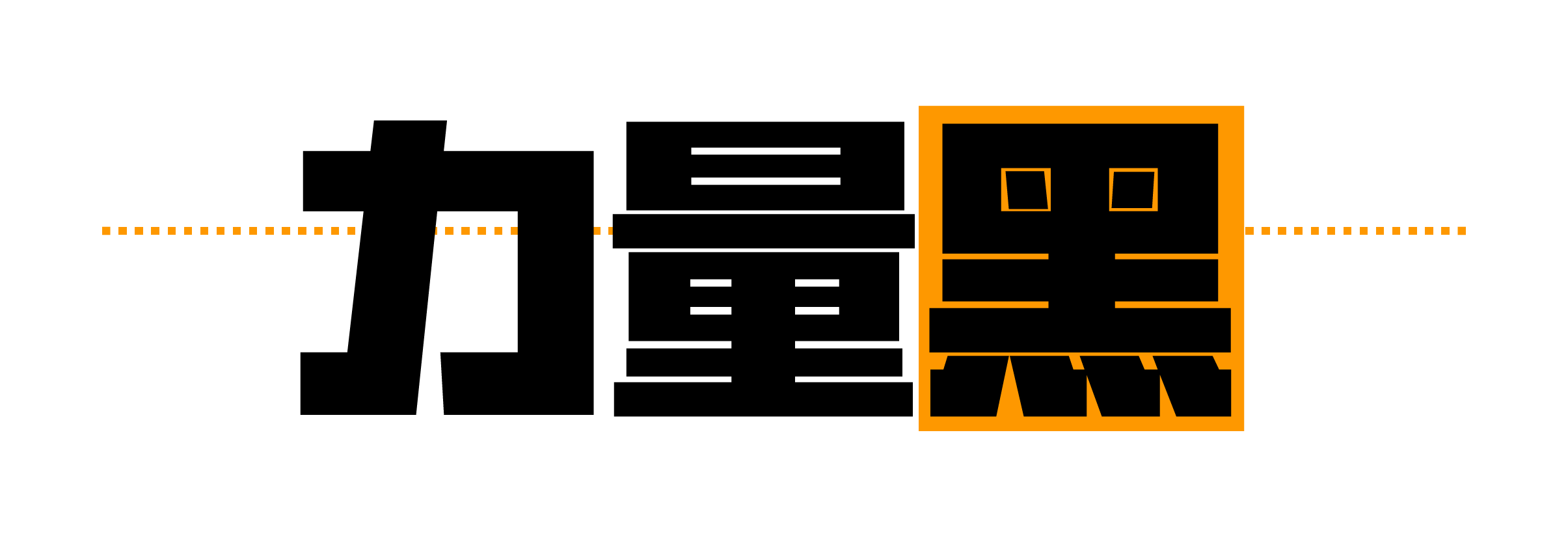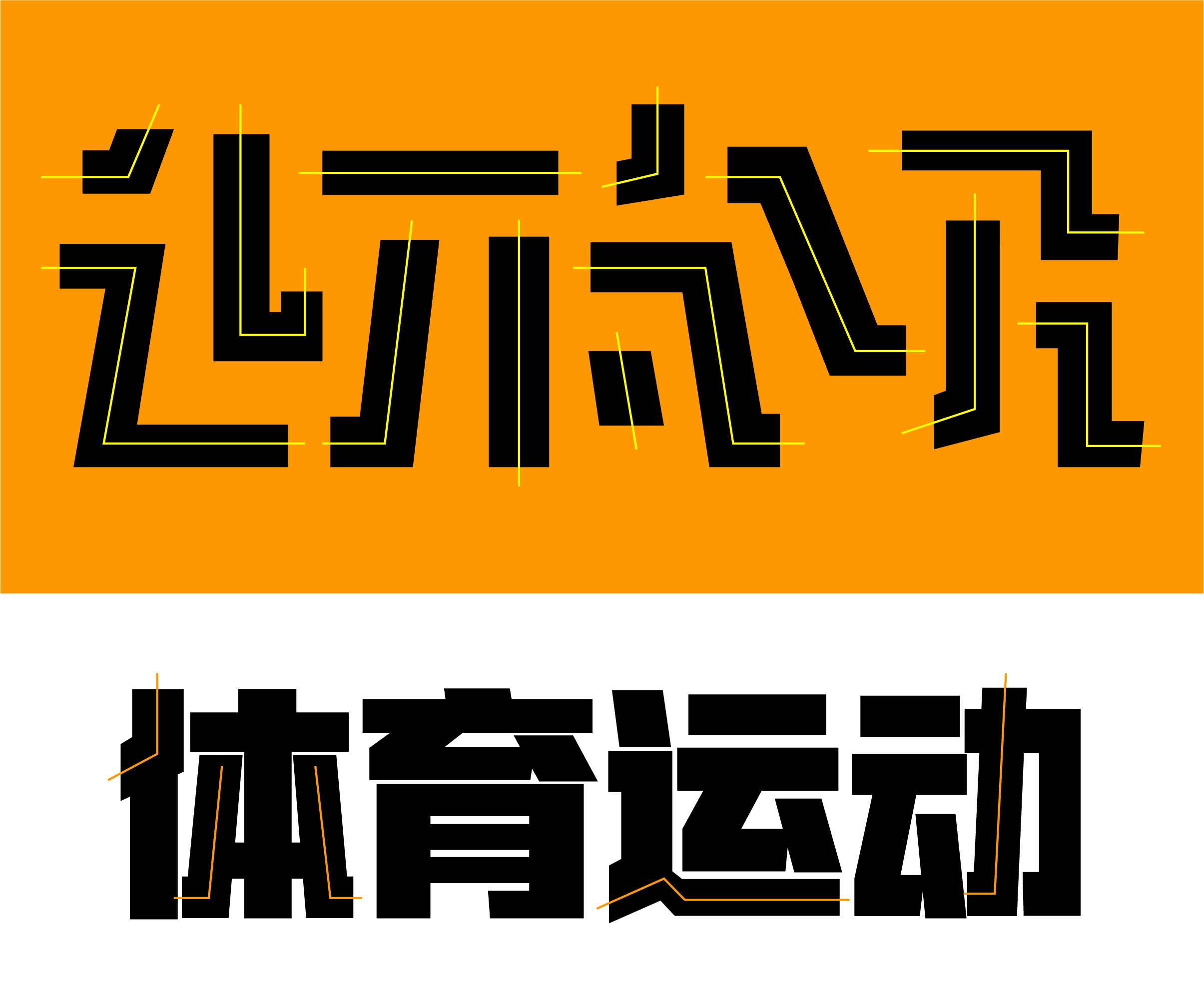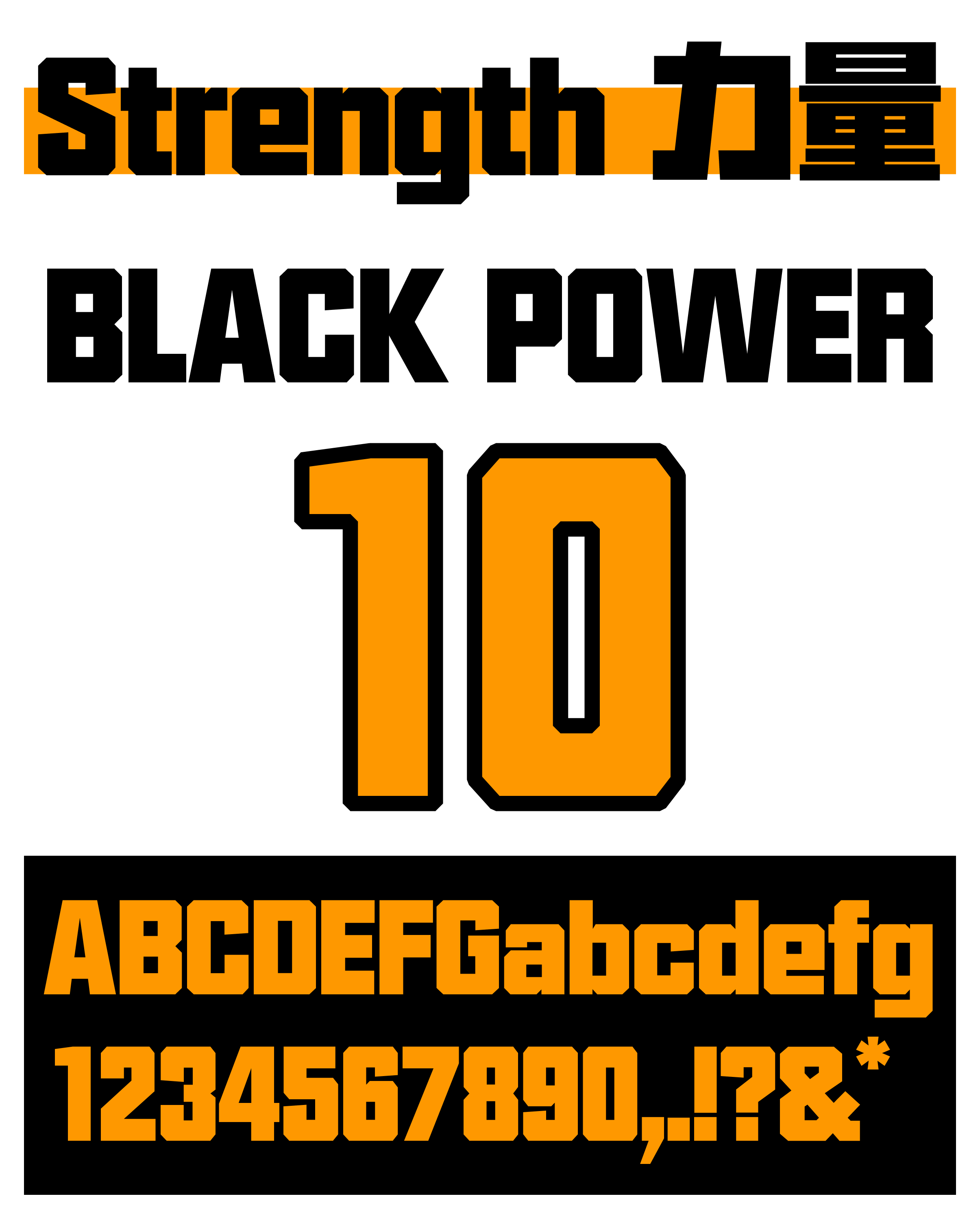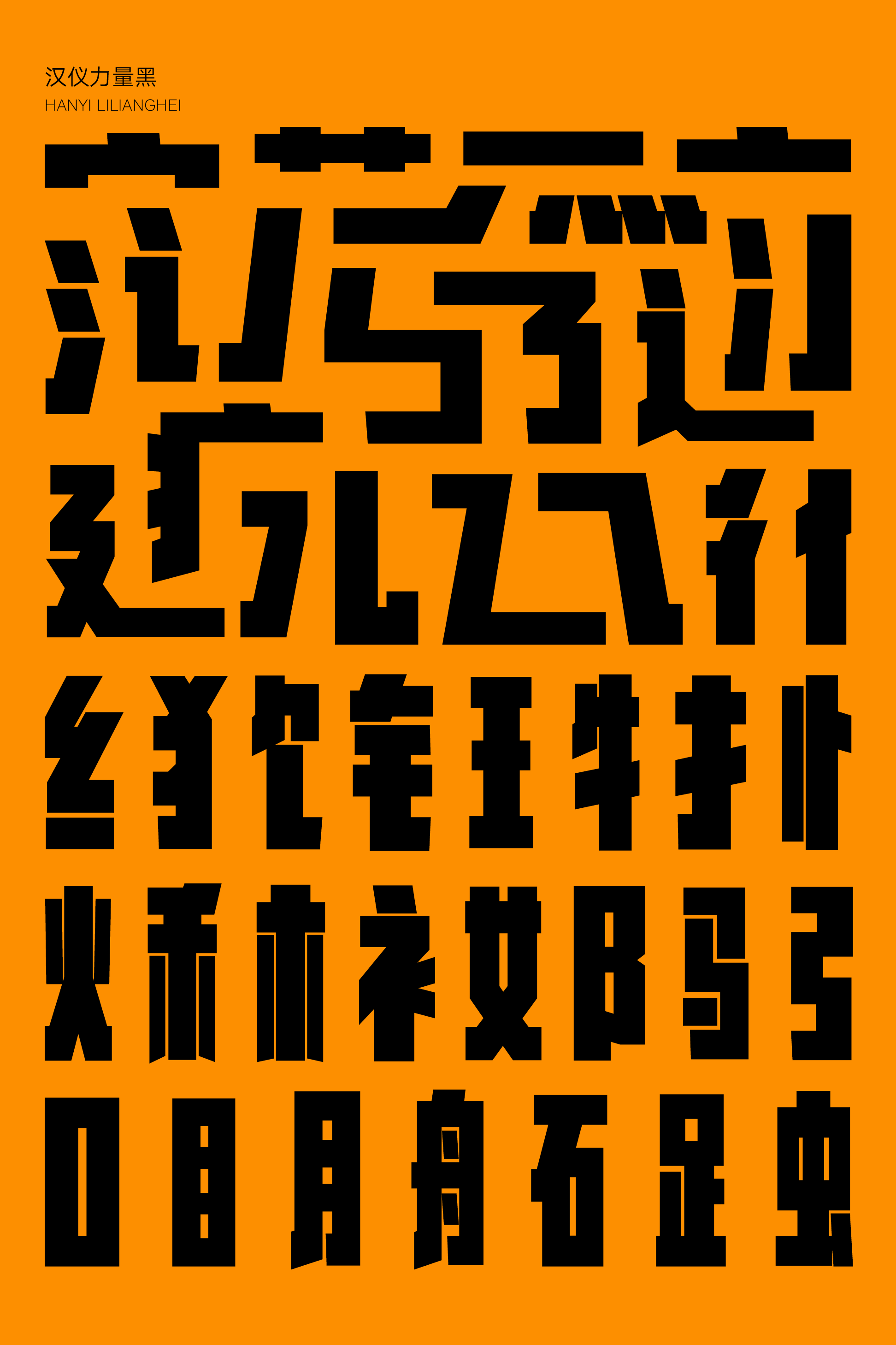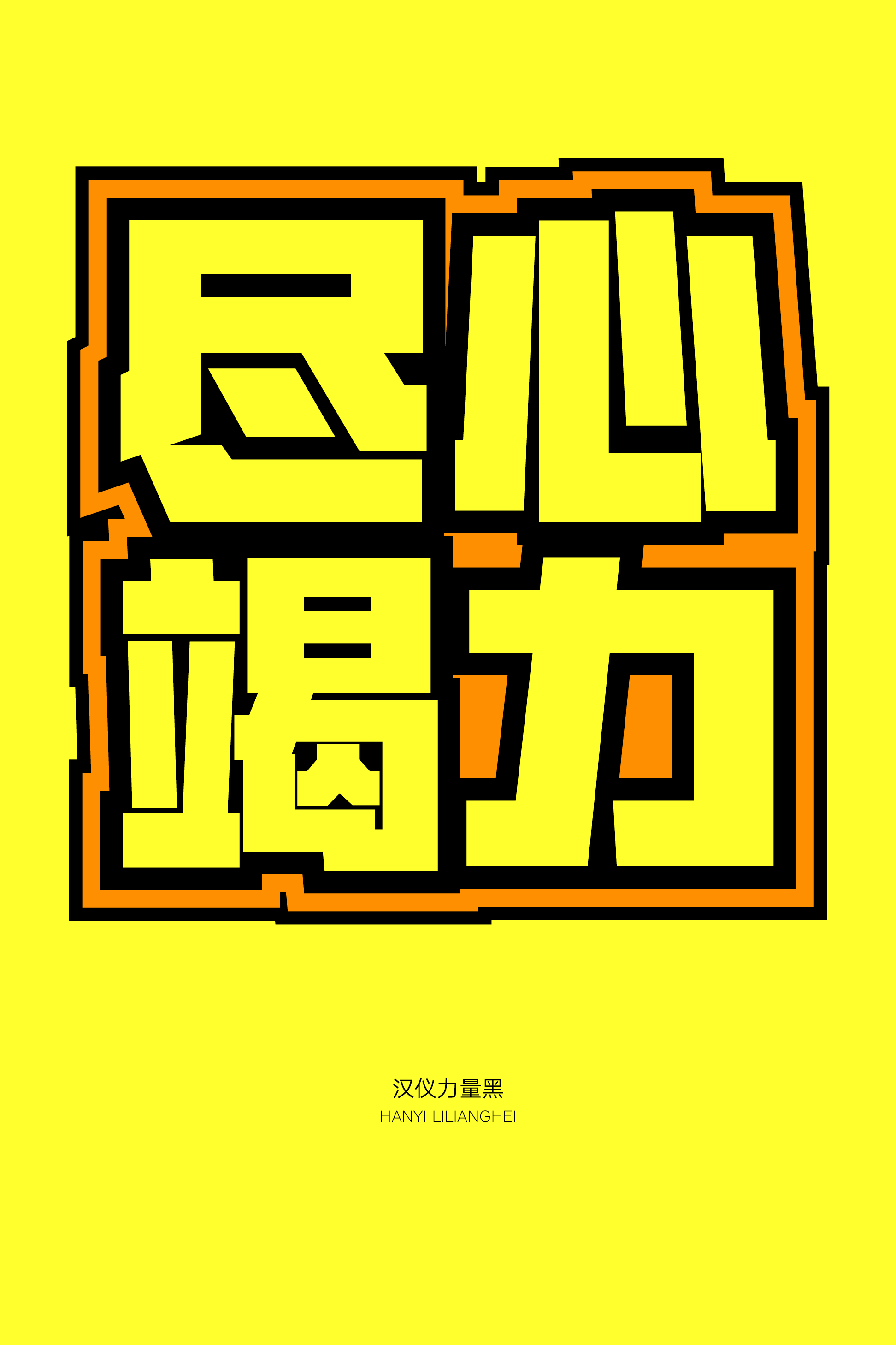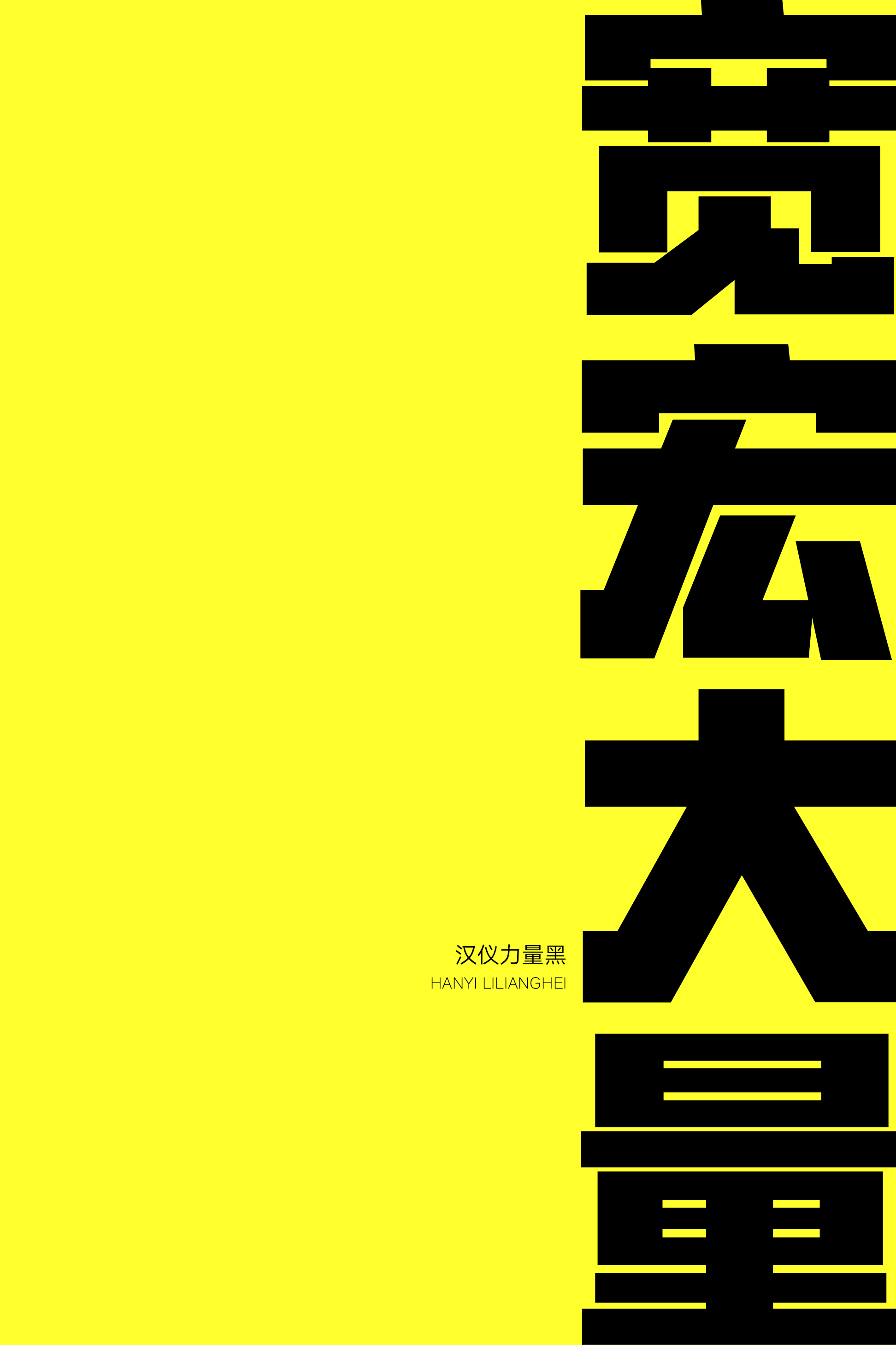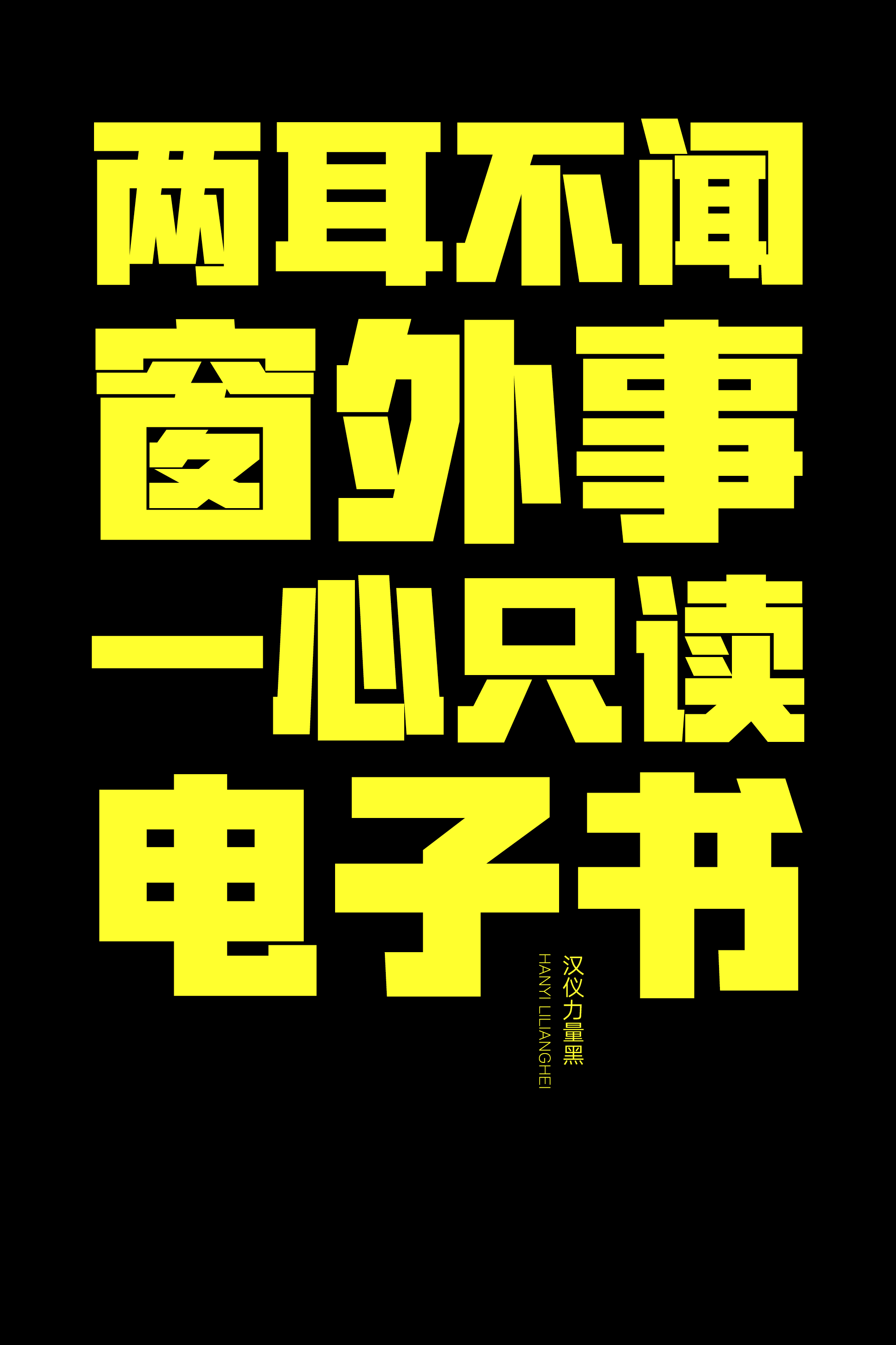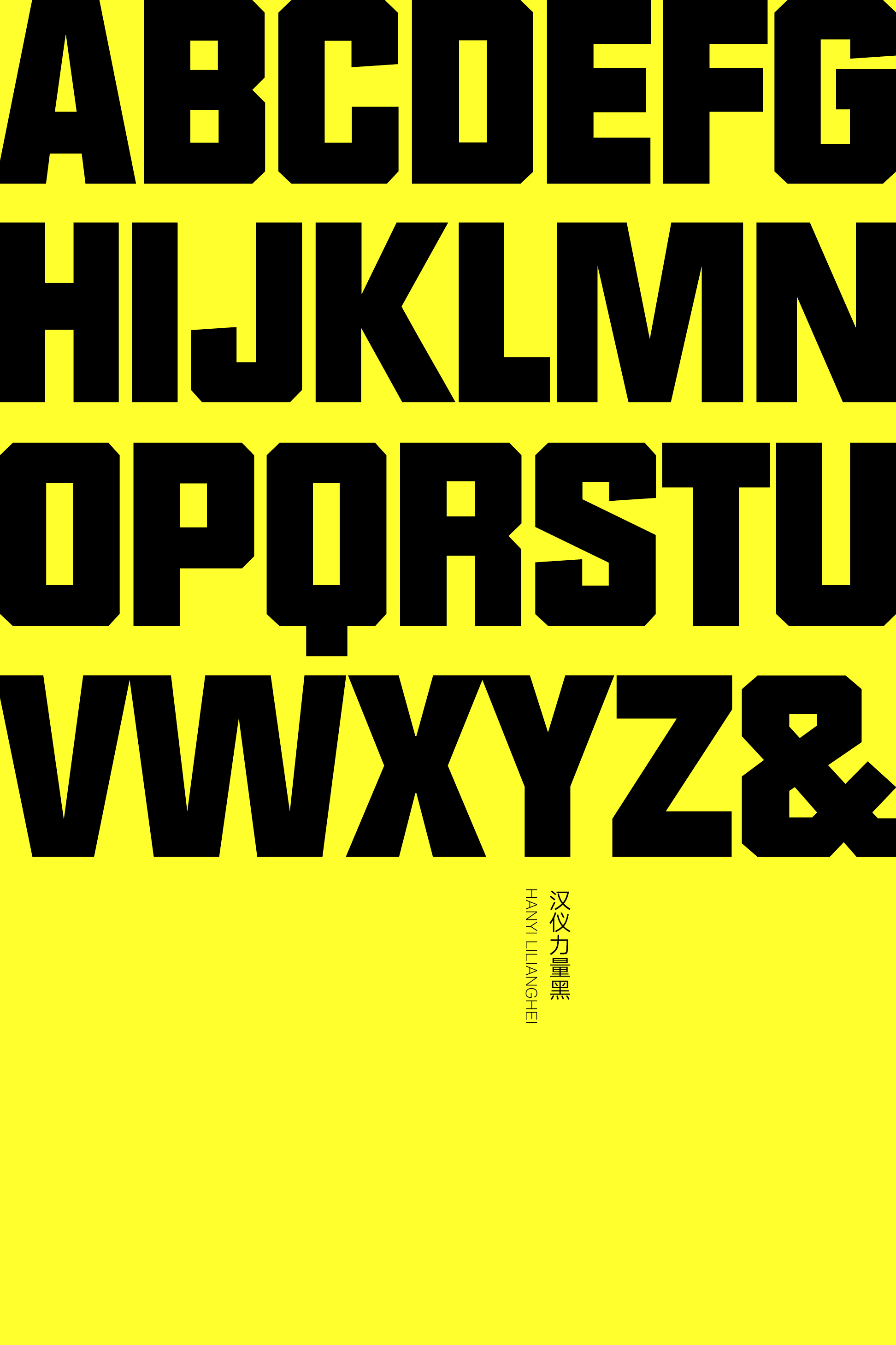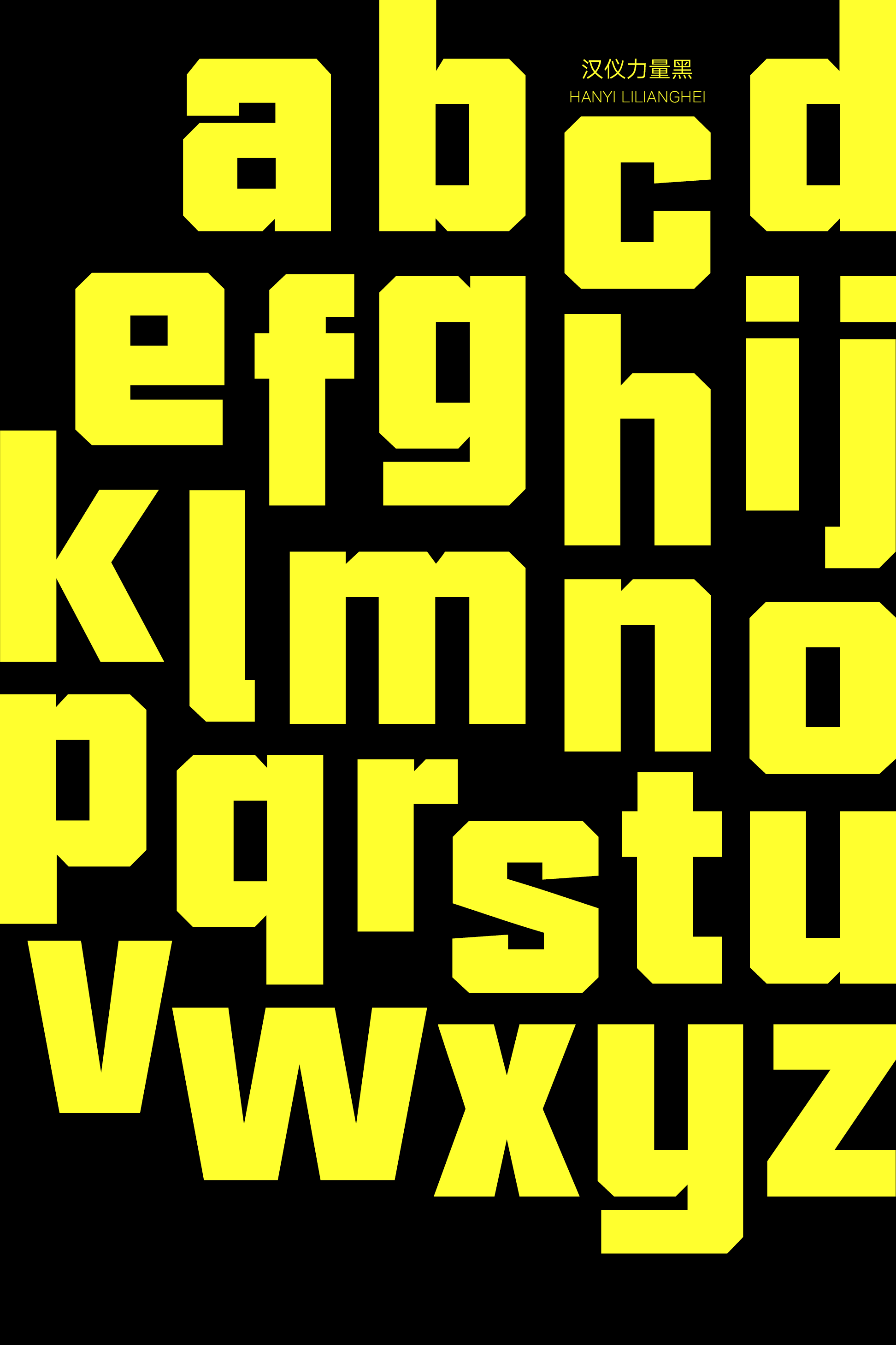
汉仪力量黑
在小小的字框内感受到大大的力量——这就是汉仪力量黑,一款具有强劲视觉冲击力的综艺风格标题字体。字形充实填满整个字框,造型硬朗,全直线的笔画构成棱角分明、坚实有力。这款字体适合应用于电商广告、产品包装、综艺影视、体育赛事等多种使用场景,重磅登场,是让人难以忽视的力量型选手。
字形呈长方形,重心偏高,饱满充实,轮廓硬朗。
方直粗黑的等线笔画,转折棱角分明、坚实有力。
将笔画间隙缩小,保留块面感和透气感。
西文部分采取同样的长方形造型,由方硬粗黑的直线构成。